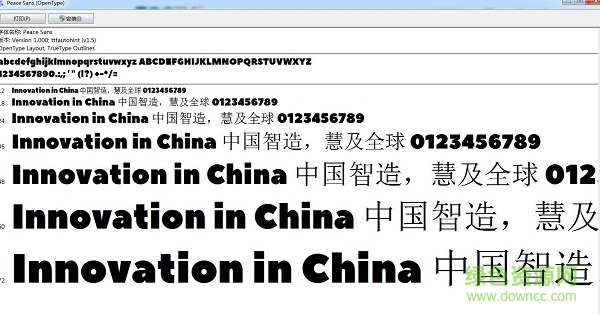
peace sans regular字體是一款線條粗壯的英文無襯線字體,又黑又圓,就像熊貓一樣圓滾滾的,十分醒目,適合用在廣告、平面設(shè)計、影視等方面,需要的朋友快來綠色資源網(wǎng)下載吧!
襯線體的筆畫在開始和結(jié)束處有額外的修飾,并且筆畫橫豎粗細(xì)不一。
非襯線體則是所有筆畫粗細(xì)一致,并且在筆畫的開始和結(jié)束處沒有額外的修飾線條。
無襯線的字體結(jié)構(gòu)簡單,在同等字號下,無襯線的字體看上去要比有襯線的更大,結(jié)構(gòu)也更清晰,所以電子設(shè)備的屏幕上也偏好使用無襯線字體。